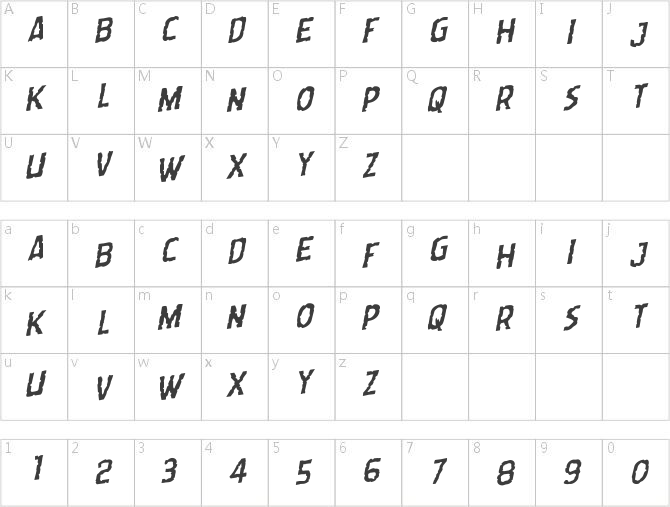
字體名稱: wormcui
wormcuisinerotal
wormcuisinerotal介紹
wormcuisinerotal字體字庫是一款讓人賞心悅目、百看不厭的英文字體,適合各類廣告和產(chǎn)品包裝設計應用,字體大小0.1MB,格式為ttf字體,上傳用戶是23KUN,作者/版權方為未知